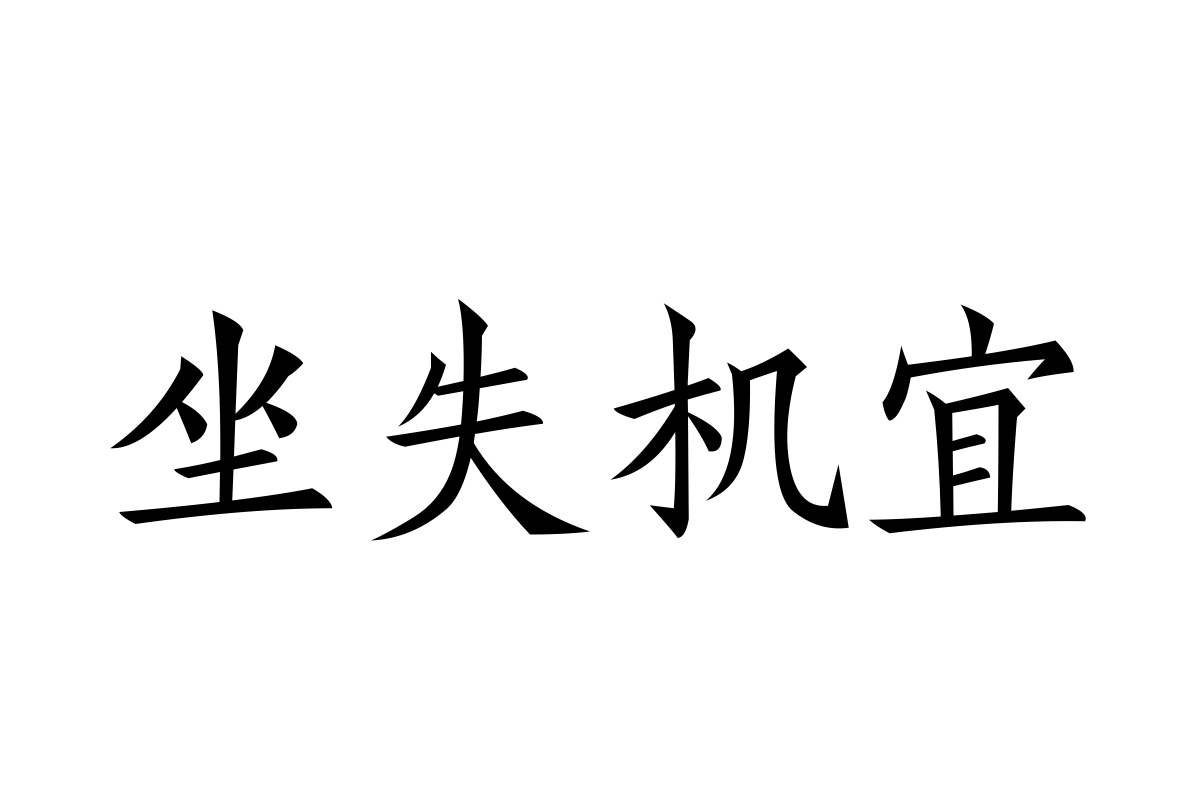
汉仪字酷堂经解楷体是一款由汉仪公司设计的字体,具有独特的风格和特点。这款字体的特点是字形简洁、线条流畅,适合用于各种需要书写和排版的场景。
1. 字形结构:汉仪字酷堂经解楷体的字形结构紧凑,笔画分明,易于阅读和识别。每个字的笔画都经过精心设计,使得整个字体看起来既有美感又不失实用性。
2. 字体风格:这款字体的风格独特,给人一种现代感和时尚感。它既保留了传统的楷书特点,又融入了一些现代元素,使得整体风格更加多元化。
3. 应用场景:汉仪字酷堂经解楷体适用于各种需要书写和排版的场景,如报纸、杂志、书籍、广告等。它的适用范围广泛,能够满足不同用户的需求。
总之,汉仪字酷堂经解楷体是一款非常实用的字体,它以其独特的风格和特点,为各种场景提供了良好的书写和排版解决方案。